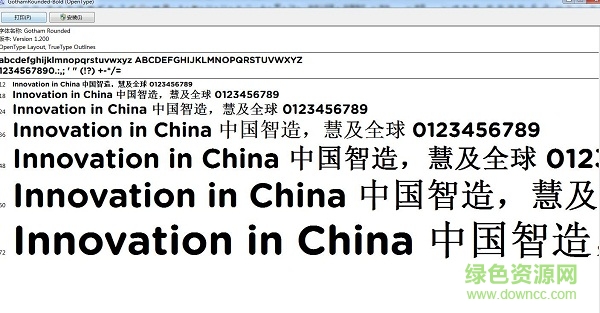
gotham rounded bold字體是一款非常粗的無襯線字體,易讀性和欣賞性兼?zhèn)?,字體活潑嚴(yán)謹(jǐn),線條偏于圓形,飽滿清晰,喜歡這類字體的小伙伴快來綠色資源網(wǎng)下載吧!
文字是用來閱讀的。比字體的外形更重要的是字體的韻律。有著優(yōu)美字母但是字距糟糕的字體閱讀性肯定很差。然而,如果字母沒有那么完美,但是他們有良好的字距,那字體也會很容易閱讀。設(shè)計韻律遠(yuǎn)比外形重要得多。